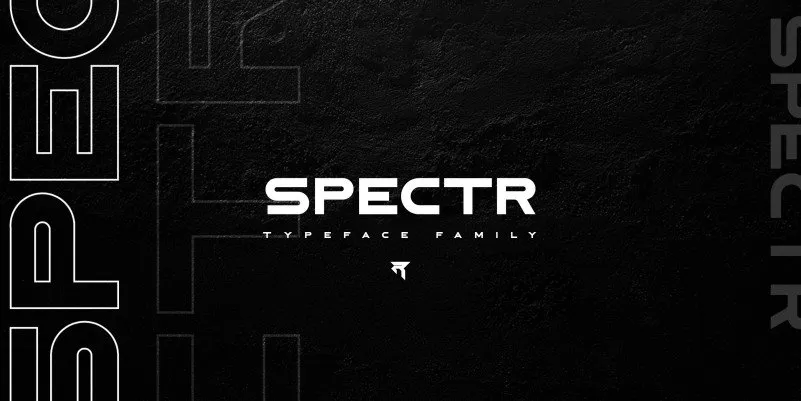
R-Spectr Sans Serif é uma fonte que combina criatividade com sofisticação ao mesmo tempo. Perfeita para designers atentos à tendência, essa fonte foi projetada para transportar os olhos pelo glamour elegante do luxo de alto padrão. A Latinotype, a empresa de fontes responsável por esta coleção inovadora, apresenta uma combinação única: elegância com um brilho incomum. Este pacote contém quatro fonts distintas que incluem linhas curvas para itálico verdadeiro e tipos regulares e esculpidos. É perfeito para criar mensagens sofisticadas e impactantes, combinando o modernismo de uma fonte sans-serif com a elegância de um estilo romanesco. Testemunhe o poder da R-Spectr Sans Serif como você redefine seu design em cada projeto.